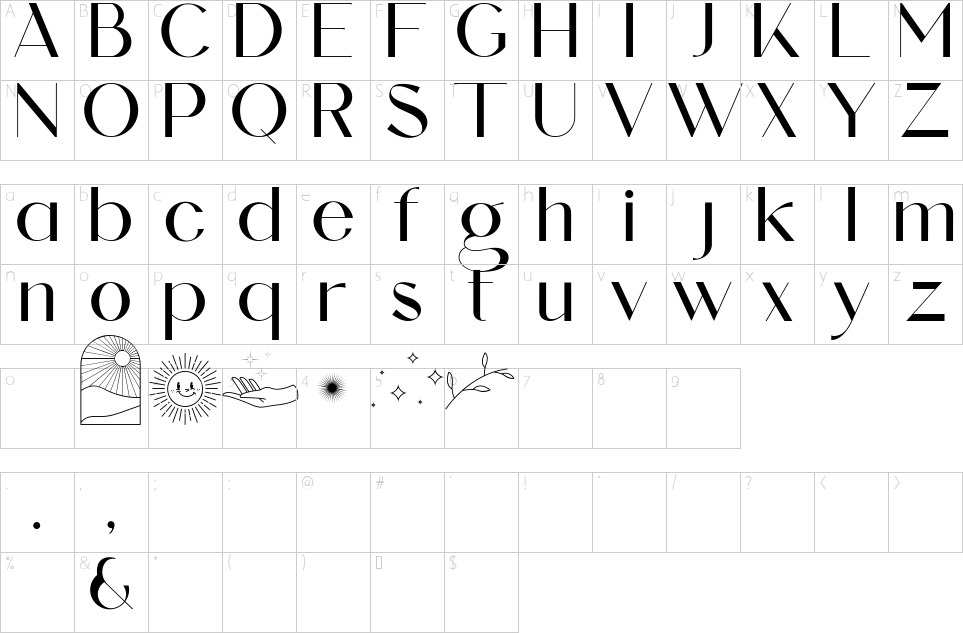
Alokary Font – Fonte Grátis
Alokary Font
Alokary é uma fonte moderna e elegante projetada por Putu Dody Permana, disponível gratuitamente tanto para sistemas Windows quanto para Mac. Com seus traços fluidos e tipografia limpa, Alokary é perfeita para projetos que exigem um equilíbrio entre sofisticação e simplicidade. Esta fonte foi adquirida 285 vezes, mostrando seu valor como uma opção de fonte de qualidade para designers e profissionais de design. Se você está procurando por uma fonte atraente que seja fácil de usar e de se integrar em diversos projetos, Alokary é uma ótima escolha para tornar sua identidade visual ainda mais única e sofisticada.